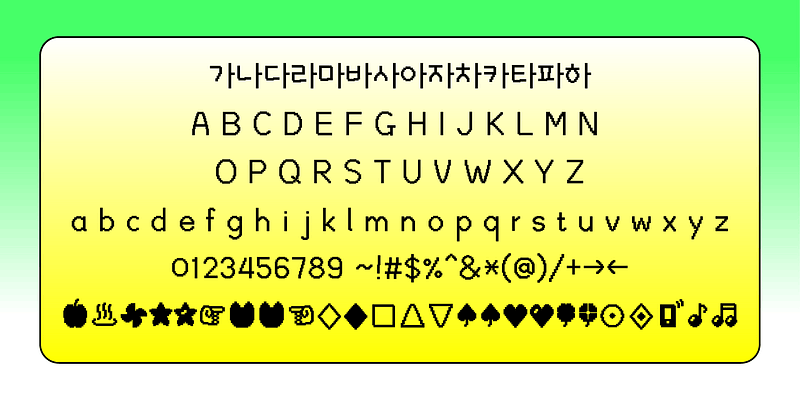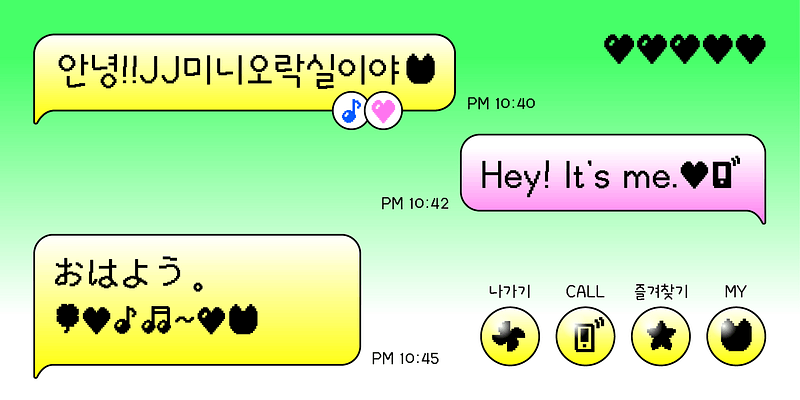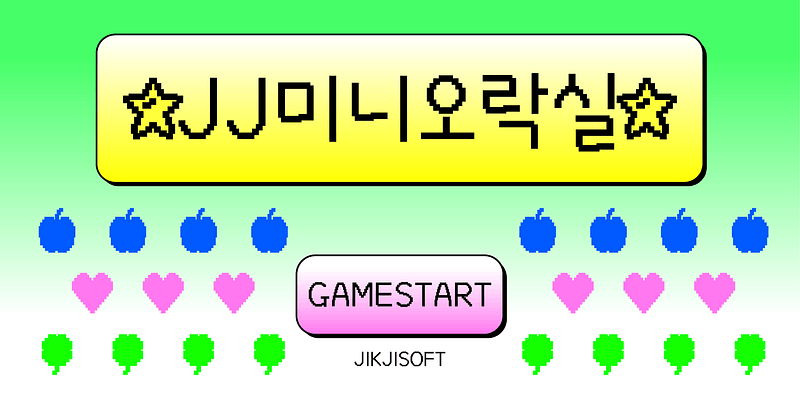
JJMiniArcade-skriften er inspirert av punktgrafikkskrifter som vekker nostalgi. Den forbedrer enkelte tegn og streker med punktgrafikkeffekter, og gir en visuell interessant og leken effekt.